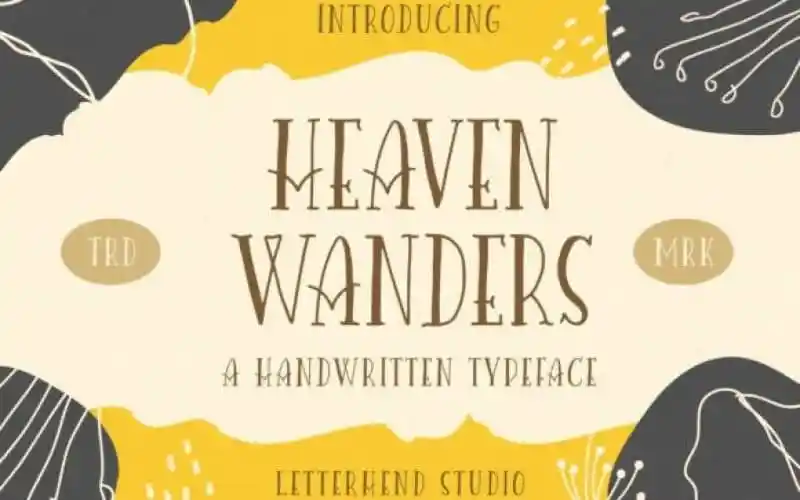
Heaven Wanders Serif Font – Fonte Grátis
Heaven Wanders Serif Font
Descubra Heaven Wanders Serif Font, uma fonte serif totalmente em maiúsculas com aparência natural e elegante. Esta fonte foi criada pela Letterhend Studio para quem procura um estilo simples e sofisticado. Com seu design de letra cuidadosamente elaborado, a Heaven Wanders é perfeita para usar tanto nas letras grandes quanto nos detalhes menores. Perfeito para criações de marca, logomarcas, headlines ou até mesmo como fundo de texto em imagens. Experimente essa fonte versátil que não decepcionará. É uma ótima escolha para tornar suas ideias ainda mais chamativas e imprimíveis. Adicione Heaven Wanders à sua biblioteca de recursos gráficos e veja como ela irá destacar seus projetos!